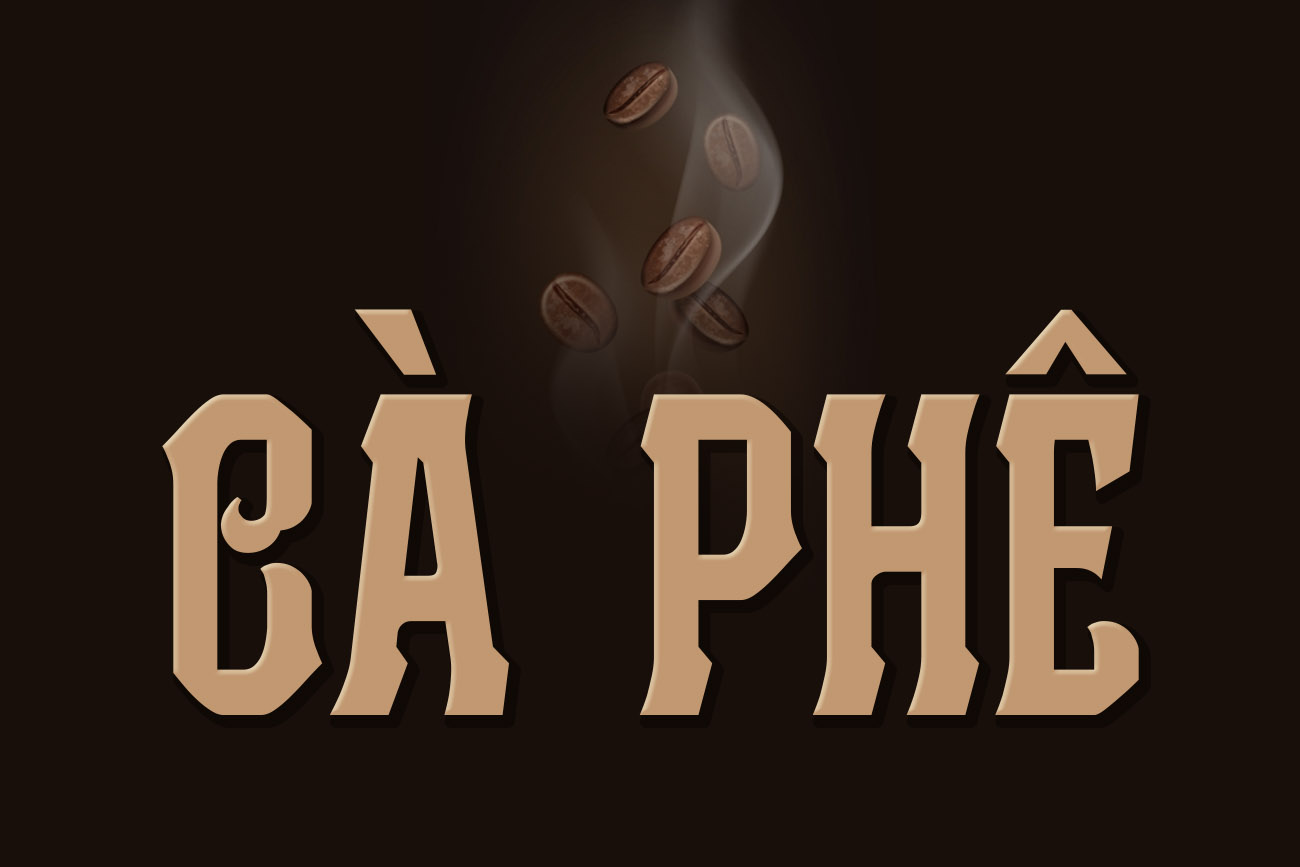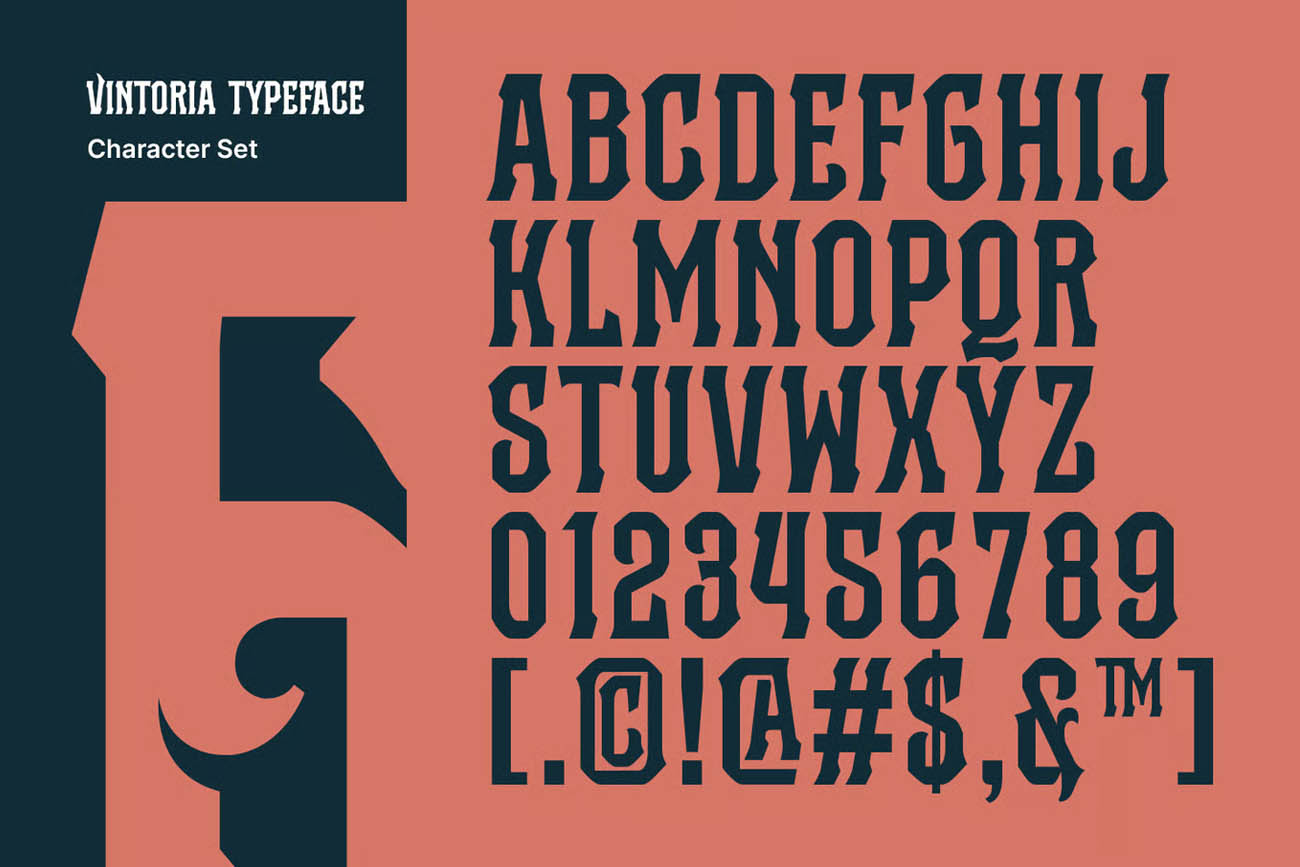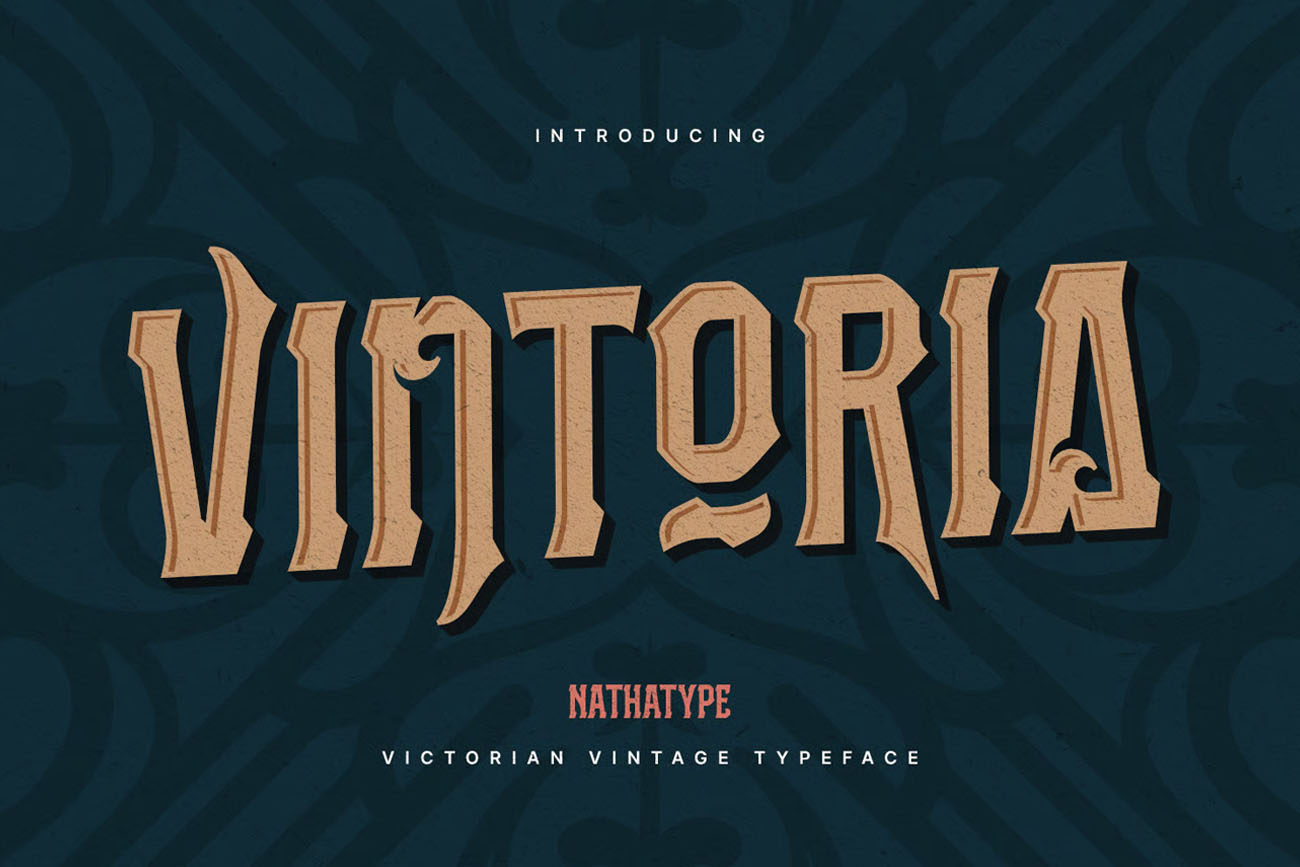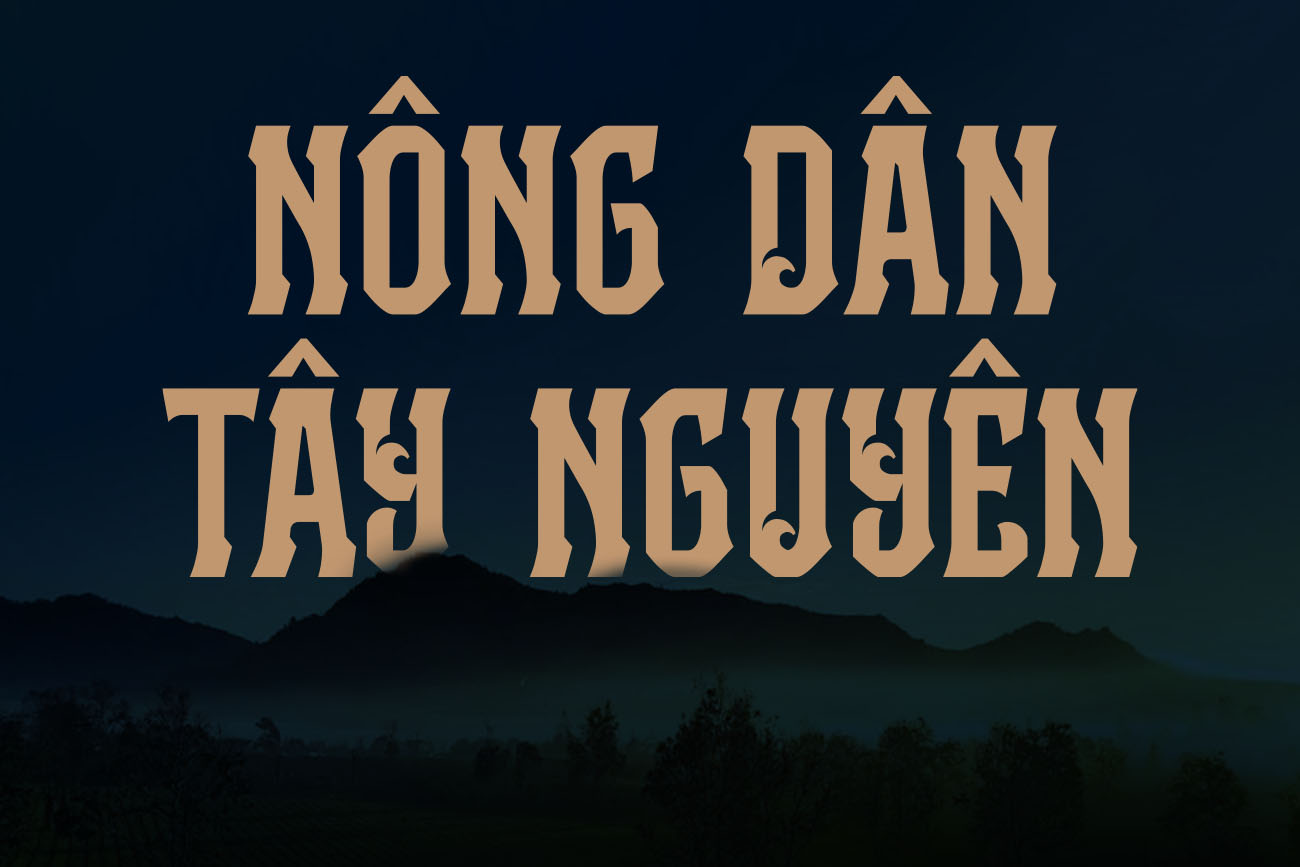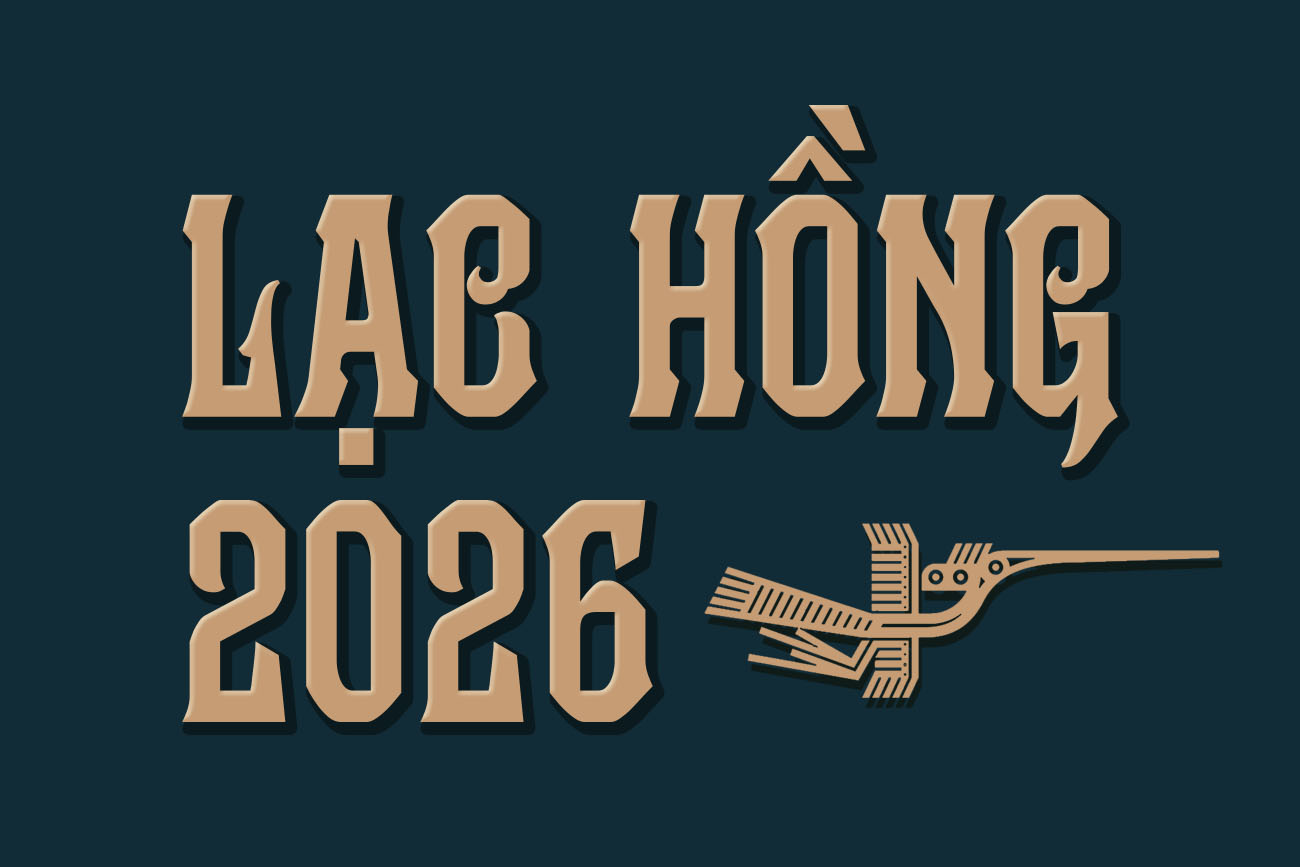
TH Vintoria – Font Chữ Vintage Mang Hơi Thở Hoàng Gia
Tác giả Natha
Trong dòng chảy không ngừng của xu hướng thiết kế hiện đại, những giá trị hoài cổ vẫn luôn giữ một vị thế độc tôn. Đối với các nhà thiết kế đồ họa yêu thích vẻ đẹp vượt thời gian, việc tìm kiếm một bộ phông chữ thể hiện trọn vẹn sự sang trọng của quá khứ là điều vô cùng quan trọng. Hôm nay, chúng tôi xin giới thiệu TH Vintoria – phiên bản Việt hóa hoàn hảo của một kiệt tác typography mang đậm phong cách cổ điển.
H Vintoria – Tuyệt Phẩm Font Chữ Vintage Mang Hơi Thở Hoàng Gia
Vẻ đẹp kinh điển từ thời Victoria
Vintoria là đứa con tinh thần của tác giả Natha, một nhà thiết kế tài năng chuyên trị các dòng chữ mang phong cách cổ xưa. Lấy cảm hứng từ thời đại Victoria (1837–1901) huy hoàng, Vintoria không đơn thuần là những con chữ, mà là sự tái hiện của nghệ thuật và văn hóa.
Điểm đặc biệt của bộ font chữ lịch sử này nằm ở hệ thống chân chữ (serif) sắc sảo kết hợp cùng những đường cong mềm mại nhưng đầy uy quyền. Nó gợi nhớ đến những tấm biển hiệu vẽ tay thủ công, những bìa sách bọc da hay các nhãn rượu vang lâu đời. Tác giả Natha đã khéo léo lồng ghép các yếu tố trang trí phức tạp vào từng ký tự, tạo nên một tổng thể vừa hoài niệm, vừa đẳng cấp.
Sự hoàn thiện của phiên bản Việt hóa TH Vintoria
Mặc dù bản gốc Vintoria rất đẹp, nhưng rào cản ngôn ngữ thường khiến các designer Việt gặp khó khăn khi xử lý văn bản tiếng Việt. Hiểu được điều này, đội ngũ TH đã thực hiện Việt hóa bộ phông chữ này một cách tỉ mỉ.
Phiên bản TH Vintoria không chỉ đơn giản là thêm dấu. Các dấu câu tiếng Việt được thiết kế và cân chỉnh kỹ lưỡng để hòa hợp hoàn toàn với cấu trúc của từng ký tự gốc. Khoảng cách (kerning) cũng được tối ưu hóa, đảm bảo tính thẩm mỹ cao nhất khi gõ các văn bản dài. Nhờ đó, người dùng có thể thoải mái sáng tạo các tác phẩm font chữ vintage chuẩn mực mà không lo vỡ bố cục hay lỗi hiển thị.
Ứng dụng trong thiết kế hiện đại
TH Vintoria là lựa chọn lý tưởng cho các dự án cần sự sang trọng và hoài cổ. Bạn có thể sử dụng bộ font chữ retro này cho thiết kế logo thương hiệu, bao bì sản phẩm cao cấp (trà, cà phê, rượu), tiêu đề tạp chí thời trang hoặc các poster sự kiện mang phong cách Classic.
Sự kết hợp giữa nét vẽ cổ điển của Natha và sự chỉn chu trong khâu Việt hóa của TH đã biến TH Vintoria trở thành một công cụ đắc lực, giúp các thiết kế của bạn không chỉ bắt mắt mà còn kể được những câu chuyện lịch sử đầy cảm xúc.